「REALTYPE(リアルタイプ)」の定額利用ができるWebフォント(一例)
▼字游工房
・游明朝体
・游ゴシック体
・游教科書体
・游筑見出し明朝体
・游勘亭流
▼凸版書体
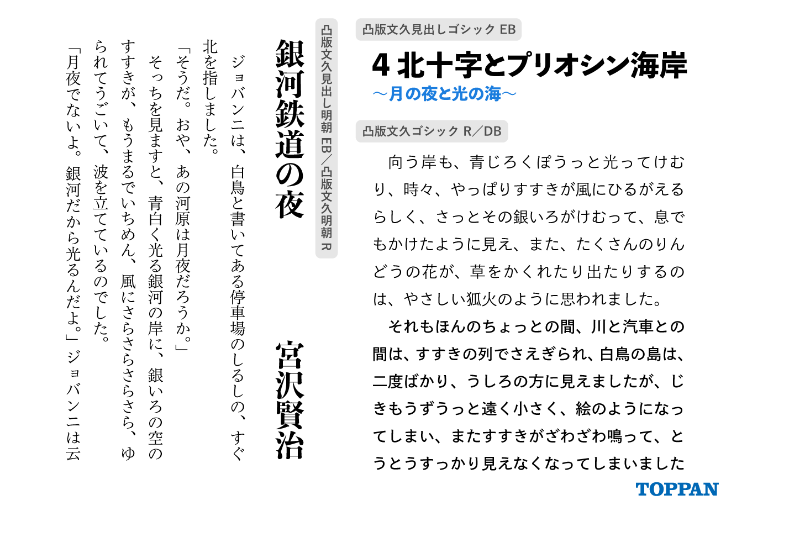
・凸版文久明朝 R
・凸版文久ゴシック R / DB
・凸版文久見出し明朝 EB
・凸版文久見出しゴシック EB
▼イワタ
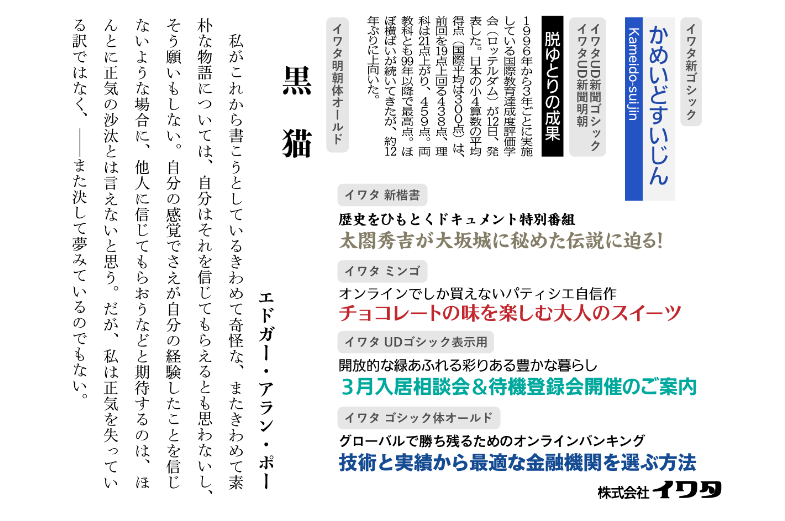
・イワタ 明朝体オールド
・イワタ 新ゴシック
・イワタ UD ゴシック表示用
・イワタ ゴシック体オールド
・イワタ ミンゴ
・イワタ 新楷書
・イワタ UD 新聞ゴシック
・イワタ UD 新聞明朝
▼砧書体制作所(旧:カタオカデザインワークス)
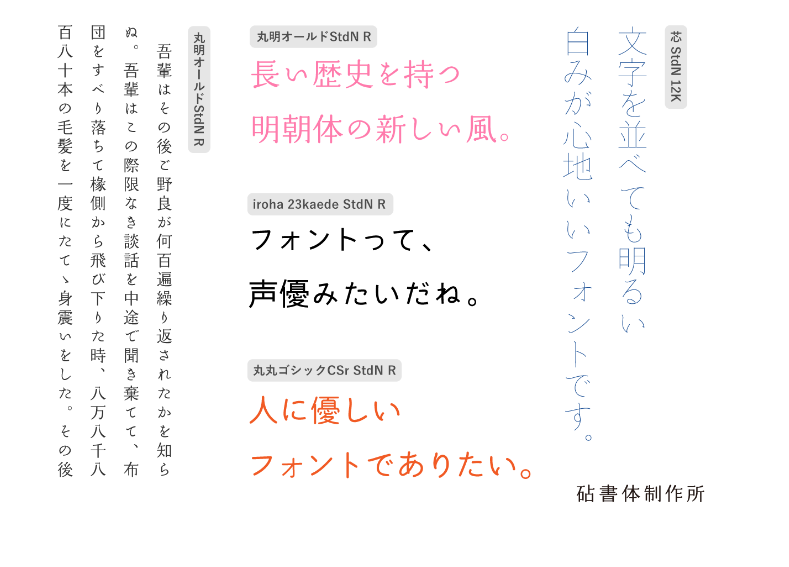
・丸明オールド StdN R
・iroha 23kaede StdN R
・芯 StdN 12K
・丸丸ゴシック CSr StdN
▼秀英体
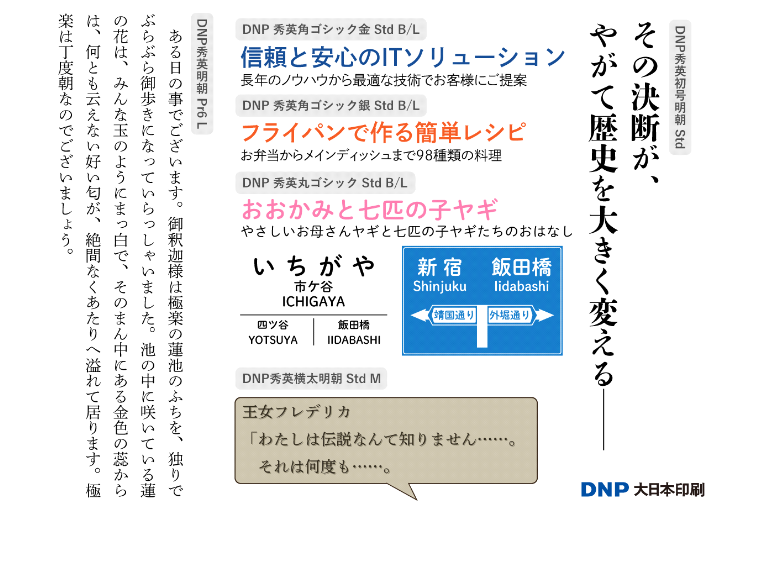
・DNP 秀英初号明朝 Std
・DNP 秀英明朝 Pr6 L
・DNP 秀英角ゴシック金 Std B/L
・DNP 秀英角ゴシック銀 Std B/L
・DNP 秀英丸ゴシック Std B/L
・DNP 秀英橫太明朝 Std M
▼タイププロジェクト
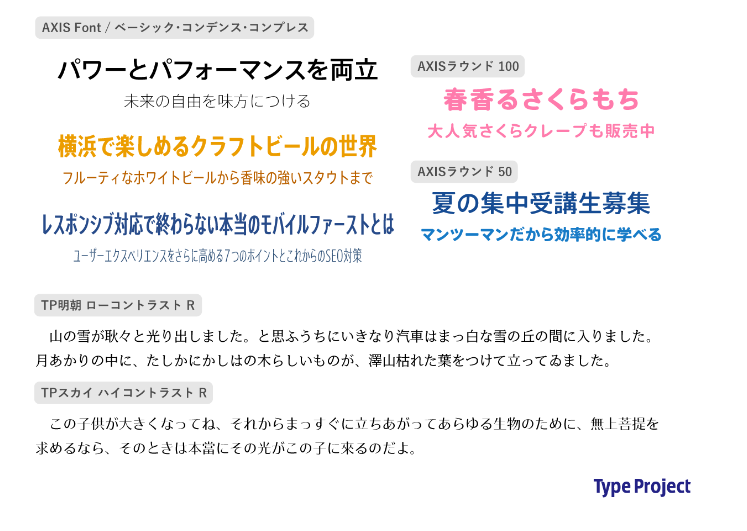
・AXIS Font / ベーシック・コンデンス・コンプレス
・AXIS ラウンド 100
・AXIS ラウンド 50
・TP 明朝
・TP スカイ